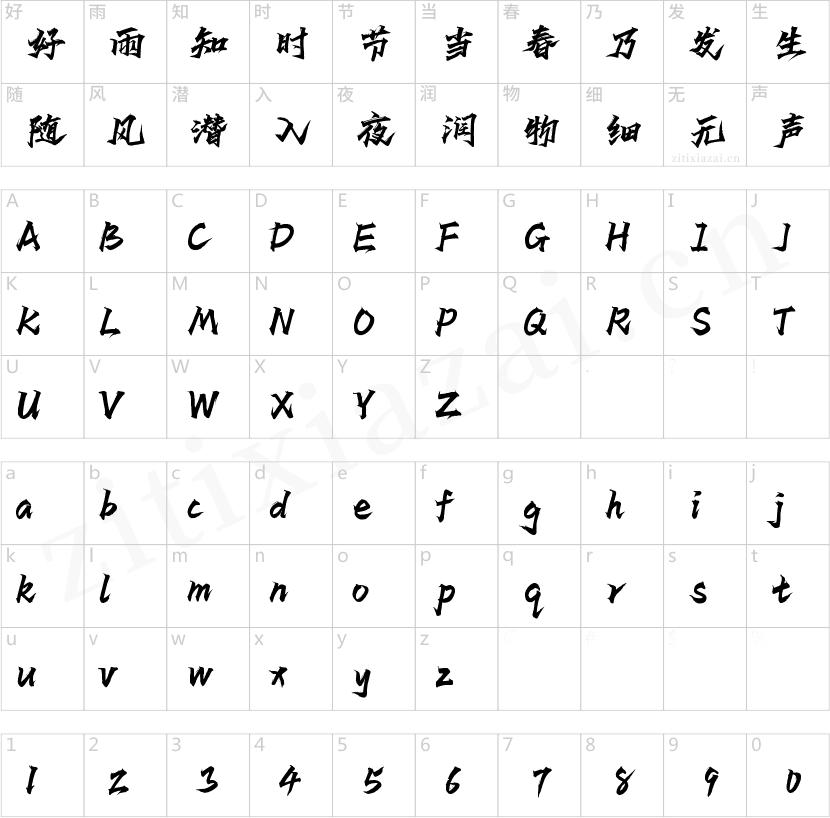
Aa丁词手书
Aa丁词手书字体
Aa丁词手书是一款非常具有艺术性的字体,它的设计灵感来源于对古典艺术的研究,同时又融入了现代字体设计的元素。字形优美,笔画粗细变化自然,给人以大气、典雅的感觉。Aa丁词手书是一款既传统又现代的字体,它的设计充满艺术感,美观大方,实用性也非常强。无论是对于设计师还是对于普通读者来说,都是一种非常不错的字体选择。Aa丁词手书适合用于具有艺术感的场合,比如海报、宣传单张、书籍封面等。由于其字形流畅且具有动态感,也适合用于大量的文本排版,如报纸、杂志等。